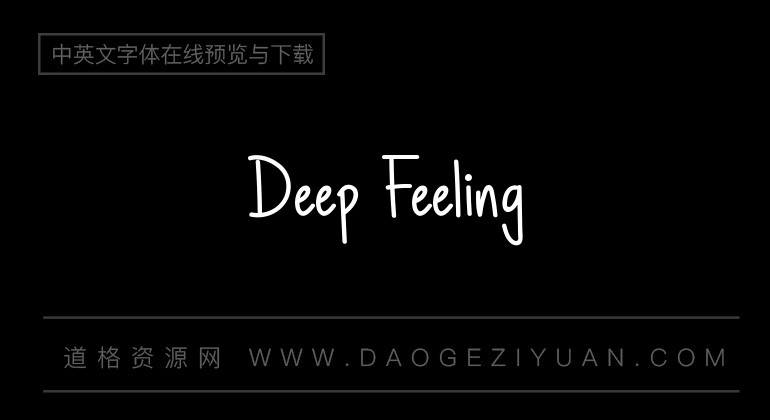
? Deep Feeling 是一款由英国设计师 Phil Garnham 于 2018 年设计的字体。它是一款简约的无衬线字体,具有柔和的外观和轻柔的质感,可以让你的文字充满深情而又不失细节。它具有独特的外观,可以使文字充满活力,令人印象深刻。Deep Feeling 字体支持多种字符集,可以用于创作网页、海报、品牌标识、绘图等等,是一款非常实用的字体。内容介绍
Deep Feeling是一款非常不错的手写艺术字体,具有很好的视觉感,适合于文化类的宣传设计、商业类品牌的广告和产品包装设计以及个性化文字排版等较多场景。